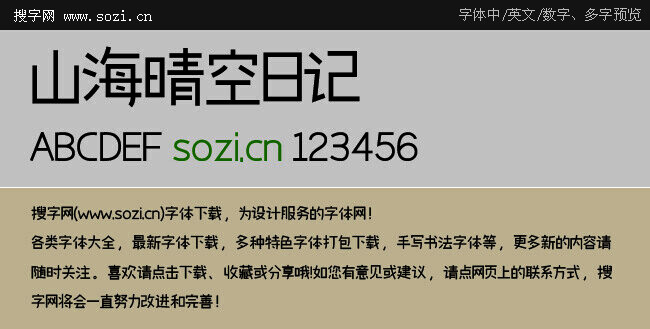
山海晴空日記
搜字網(wǎng)提供一款山海晴空日記中文藝術(shù)字體下載,山海晴空日記是一款卡通風(fēng)非襯線字體,包含漢字簡體6763個。字體童趣可愛,結(jié)構(gòu)多變靈動,字形活潑清新,造型生動有趣,線條靈動均勻,直線與弧線的完美結(jié)合,使字體具有靈活的適用性,天真俏皮又不失時尚感。適合包裝設(shè)計、海報設(shè)計、廣告設(shè)計等應(yīng)用。